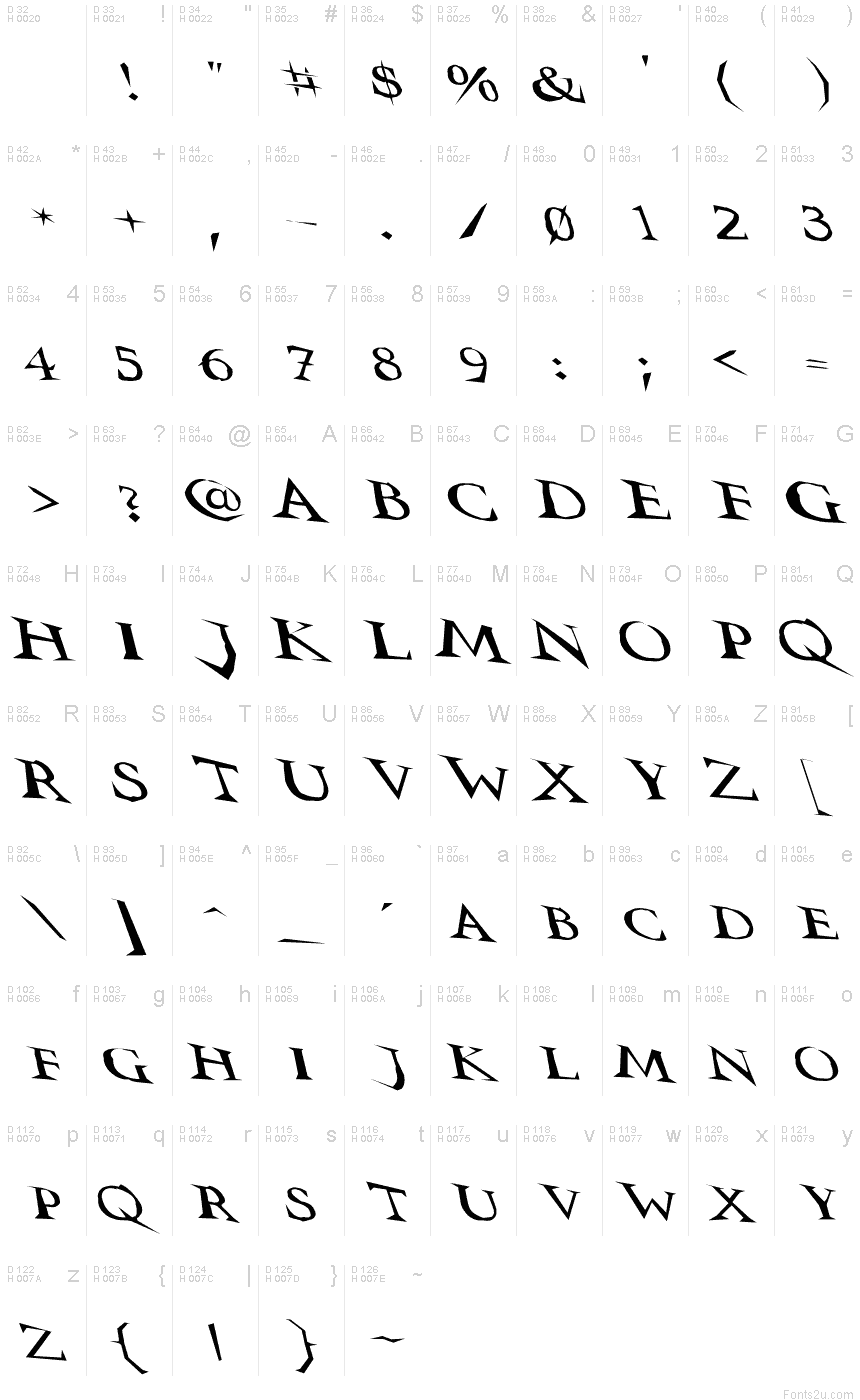
Podgląd czcionki VTCSwitchbladeRomanceSloppyDrunk
VTC Switchblade Romance Sloppy Drunk od V.T.C. Vigilante Typeface Corporation to darmowy font składający się z przerysowanych rzymskich wersalików o chwiejnym, nocnym charakterze. Litery przechylają się i chwieją, z ostrymi, klinowatymi szeryfami, rozciągniętymi łukami i nierównym rytmem, dzięki czemu klasyczny styl inskrypcji wydaje się jednocześnie elegancki i rozpadający się.
To naturalny wybór do nagłówków plakatów, okładek książek w stylu pulp, ulotek barowych, kart tytułowych i logotypów zespołów, gdzie darmowy font może szybko dodać teatralnej niestabilności. Użyj go, gdy chcesz, aby wielkie litery wydawały się wyrafinowane, ale niekoniecznie trzeźwe – to krój pisma idealny do dramatycznych nagłówków na okładkach lub monogramów z przebiegłym, lekko niebezpiecznym zacięciem.